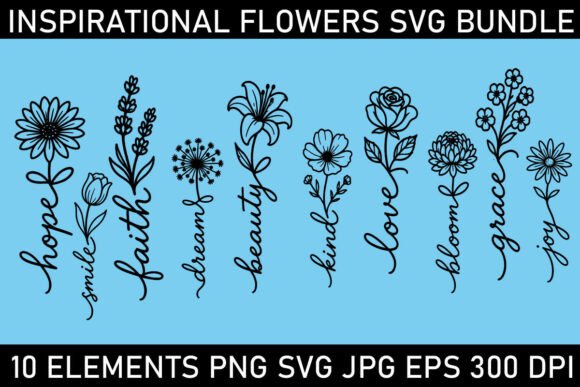
Inspirational Flower Words SVG Bundle
Encontrar los elementos de diseño adecuados puede ser un desafío, pero Inspirational Flower Words SVG Bundle ofrece una colección excepcional que eleva tu trabajo al instante.
Elaborado con precisión, Inspirational Flower Words SVG Bundle proporciona vectores limpios, tipografía suave y una licencia comercial para tu tranquilidad.